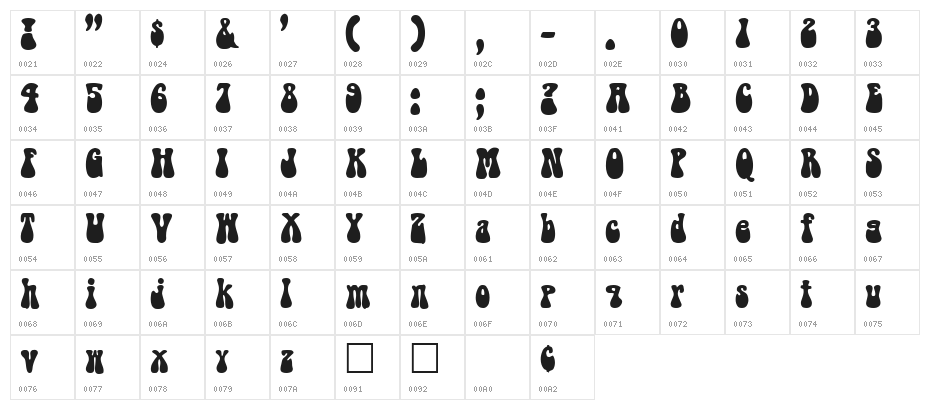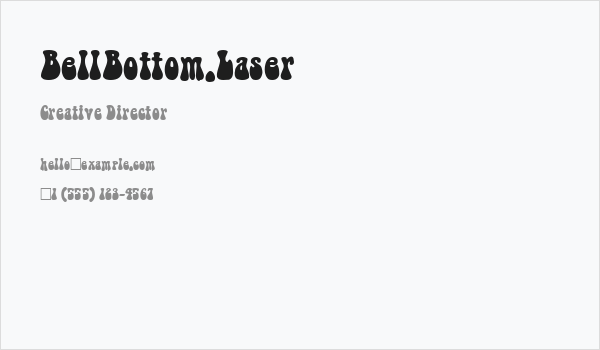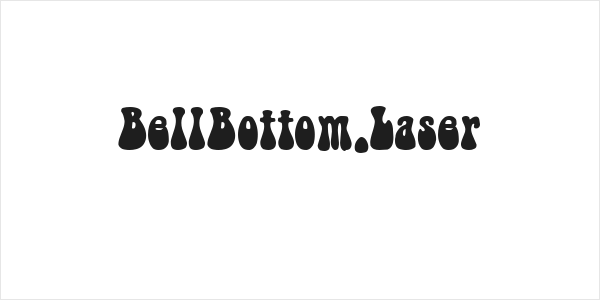
BellBottom.Laser Font
Fonts by Altsys Metamorphosis
| Proiecte propuse | Ideal for retro-themed posters, album covers, event flyers, and branding that seeks a playful and nostalgic touch. |